[동네책방의 매력] 2. 식물이 있는 동네책방, 오버그린파크
“잠시 쉬어 갈 수 있는 비밀스러운 동네책방”
그저 옷이 좋아 패션회사에서 일을 시작했던 그녀는 어느 순간, 빠르게만 흘러가는 서울 생활이 힘에 겨웠다. 평소 좋아했던 식물, 책과 더 밀접하게 지내고 싶어 오래된 동네에 아지트 같은 책방을 차렸다. ‘동네책방의 매력’ 기획연재의 두 번째 책방 ‘오버그린파크’의 주인 손예서 대표의 이야기이다. 오버그린파크는 전혀 책방이라고는 없을 것 같은 길목에 갑자기 등장해서 비밀스럽고 반갑다. 초록의 식물들이 숨 쉬는 싱그러운 공간에서 그녀와 함께 식물과 책에 대한 이야기를 나눴다.
어떻게 책방을 차리게 되셨나요?
서울에서 직장생활을 하면서 도시의 바쁨이 적응이 안 됐어요. 몸담았던 패션회사 같은 경우도 트렌드의 접점에 있다 보니 점점 버겁다는 느낌이 들더라고요. 일을 그만두고 조용하게 천천히 운영할 수 있는 공간을 갖고 싶었죠. 제가 문학을 전공했고, 원래부터 글을 쓰고 싶어했거든요. 아무래도 책을 다루다 보면 글을 좀 꾸준히 쓸 수 있지 않을까 싶어서 열게 되었어요.
‘오버그린파크’라는 책방의 이름은 어떤 뜻인가요?
큰 의미가 있는 것은 아니고, 도시 속의 공원 같은 컨셉을 생각해서 키워드를 나열해보다가 짓게 되었어요. 저는 오버그린파크가 동네 아지트 같은 곳이었으면 좋겠어요. 갖춰진 것은 조금 미흡하더라도 이곳에서 편하게 쉴 수 있는 그런 곳이요. 오셔서 책 보시면서 본인 작업을 하셔도 괜찮아요.
식물과 책을 컨셉으로 하게 된 이유는요? 둘 사이의 공통점이 있을까요?
단순히 제가 좋아해서 같이 두게 되었어요. (웃음) 식물과 책은 큰 변화가 있는 것은 아니지만, 분명히 사람과 교감이 작용한다는 공통점이 있어요. 평소에 접하는 영화나 TV 같은 매체는 정말 다양한 움직임이 있고 눈에 띄게 변화가 보이잖아요. 그에 비해 식물은 가만히 있는 것 같죠. 물론, 식물도 성장하지만 워낙 느리니까 거의 고정적으로 보이죠. 책의 텍스트도 그대로 있고요. 둘 다 겉으로 보기엔 변하지 않아도 사람과 소통하면서 오는 교감이 있는 것 같아요.
들어오자마자 식물을 먼저 살펴봤는데, 잎이 촉촉하더라고요. 물을 주신 건가요? 하루 일과는 어떻게 되시는지 궁금해요.
오시기 전에 물을 한 번씩 주었어요. 식물이 잘 자라기 위해서 온도는 18~27도 사이로 일정하게 유지하려고 하고 있고요. 먼저 아침에는 문을 활짝 열어놓고 환기를 시켜요. 식물에 환기가 중요해서요. 그다음 식물을 일일이 살펴보면서 물을 주고요. 흙이 많으니까 먼지가 자주 쌓여서 책에 먼지도 닦아줍니다. 인터넷으로 신간과 책에 관한 동향도 살피고요. 식물도 트렌드가 있어서 관련 자료를 조사하고 SNS와 홈페이지를 관리하면 하루가 금방가요.
식물과 책은 대략 어느 정도 있을까요?
식물은 70종 정도, 책은 150종에서 200종 정도 있는 것 같아요.
책은 어떤 기준으로 큐레이션 되나요?
우선 식물 관련 서적이 메인이에요. 책을 큐레이션을 할 때는 누구나 읽기 쉽고 접근하기 쉬운 책들 위주로 고르고, 너무 전문적인 책들은 배제하고 있어요. 아무래도 고객층이 식물을 처음 키워보고 접근하시는 분들이 많아서요. 문학 서적들은 순전히 제 취향이지만, 식물 서적과 마찬가지로 읽기 쉬운 책들로 배치하고 가벼운 내용이나 사랑 이야기가 담긴 내용은 제외하고 있어요. 참, 기존 서점에서 베스트셀러라고 하는 책들은 없어요.
그럼 지금까지 가장 많이 팔렸던 책은 무엇인가요?
대니얼 샤모비츠의 <식물은 알고 있다>라는 책이요. 이 책은 식물을 좋아하시는 분들도 사가시고 식물에 관심이 없는 분들도 재미있게 읽으시는 것 같아요. 주로 식물 종류에 대해서 알려주는 책이 많은 편인데, 이 책은 식물이 어떻게 느끼고 보고 반응하는지 그런 감각에 대해 말하고 있어요.
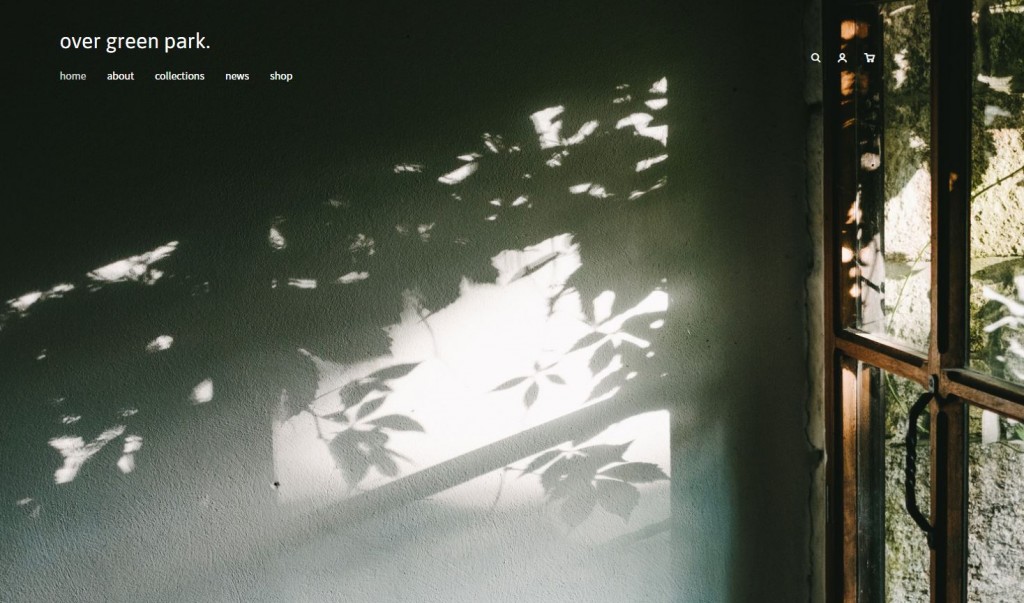
▲ 오버그린파크 홈페이지 캡쳐
오버그린파크 로고로 쓰이는 폰트는 무엇인가요?
지금 유리에 붙어져 있는 로고는 예전에 쓰던 것이고요. 홈페이지에 있는 게 앞으로 쓸 로고예요. ‘Noto Sans CJK KR‘이라는 폰트에요. 무료 폰트 중에 가장 무난하게 사용할 수 있는 것을 선택했어요.
왜 노토산스를 선택했나요?
사실 제가 전문가가 아니어서 말하는 게 맞는지 모르겠지만, 공간을 운영하며 추구하고 싶은 이미지가 다양할 거로 생각했거든요. 밝은 느낌일 때도 있지만 한 가지에만 머물고 싶지 않아서 폰트는 개성이 강하지 않아야 한다고 생각했어요. 보통의 느낌으로 일관성을 주기 위해서요.
▲ ‘오버그린파크’가 있는 골목
책방의 위치를 당산동으로 자리 잡으신 이유가 있나요?
일단 조용하고 느리게 가는 공간을 지향하고자 했어요. 그러다 보니 조금 숨어있는 장소를 찾고 싶었죠. 오래된 골목 같은 곳을 위주로 보았고, 접근성도 고려했어요. 당산동이 지하철이나 교통이 잘 되어있으니까요. 처음에는 서교동 같은 번화가도 생각했지만 컨셉을 고려했을 때, 사람들이 덜 붐비는 곳으로 선택하게 되었어요.
제가 당산에서 20년을 살았는데, 이런 골목안에 이렇게 좋은 책방이 있는 줄은 몰랐어요. 이사 가서 아쉬워요.
그런데, 저희 책방이 좀 호불호가 갈려요. 혹평하시는 분들은 혹평하시더라고요. 반면에 이런 느낌을 좋아하시는 분은 자주 오시고 그래요. (웃음)
동네 주민이면서 단골손님도 계신가요?
네. 20대 후반 정도 되는 여성분도 있고 2, 30대 남성분도 꽤 종종 오세요. 거의 매주 오시는 분도 있어요.
자주 오시는 분들이 계신다는 게 참 보람찰 것 같아요.
맞아요. 매주 오시는 분은 원래 식물에 관심 없던 남자분이셨어요. 이 동네에 젊은 느낌의 가게가 없어서 신기해하며 들어오셨다가 식물을 한번 사가시고 마니아가 되셨거든요. 작년 가을에 첫 구매를 하셨는데, 지금은 집에 40종이 넘는 식물이 있다고 해요. 각각의 모양도 다르고 키우는 재미를 느끼신 것 같아요. 제가 식물입문의 길을 안내해드린 것 같아 뿌듯했어요.
원데이 가드닝, 북클럽 같은 워크숍도 열리더라고요. 기획하시는 이유가 있나요?
원데이 가드닝 워크숍 같은 경우에는 시중의 가드닝 수업의 가격이 비싸서 진입장벽이 높은 것 같다고 생각했어요. 취미로 재미 삼아 부담 없이 할 수 있게 되길 바라며 만들었어요. 보통 한 달에 4, 50명 정도는 들으시는 것 같아요. 책 읽기나 독서모임 같은 경우는 비슷한 생각을 하는 사람들과 교류하고 싶은 마음에서 열었는데, 개인 일정상 올해 봄까지만 운영했어요.
대표님의 인생 책은 무엇인가요?
이성복 시인의 <무한화서>라는 책이에요. 시론집인데요. 엄청 긴 산문이 아니라 짧은 두세 문장으로 시에 관련된 얘기들을 적어놓으셨는데, 이 내용이 문학에만 국한된 얘기가 아니라 인생과도 맞닿아 있어서 참 좋아요.
마지막으로, 오버그린파크는 어떤 책방일까요?
휴식을 취할 수 있는 곳이라고 생각해요. 다른 사람 눈치 안 보고 편안하게 있을 수 공간이요. 저도 손님께 말 걸고 그런 스타일도 아니고요. 오시는 손님도 그렇게 많지 않은 동네니까 더욱 편하게 있으실 수 있을 것 같아요.
손예서 대표가 생각하는 동네책방의 매력
“우선 동네책방은 부담갖지 않고 편하게 갈 수 있고, 요즘은 책방마다 추구하는 컨셉이 있잖아요. 책방 마다 컨셉을 담은 큐레이션이 가장 매력적인 것 같습니다.”
– 오버그린파크 대표 손예서